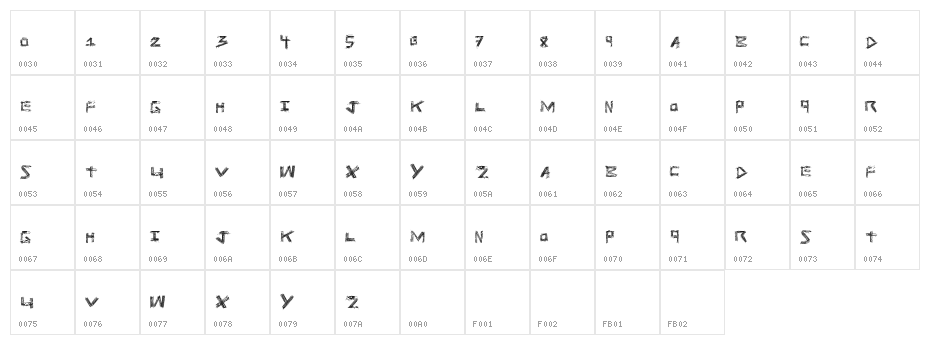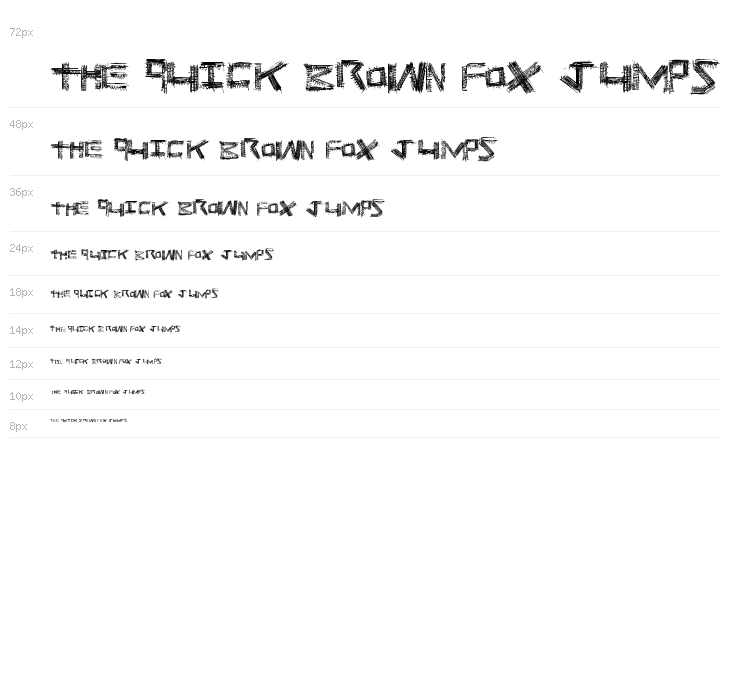
PrisonBreak Font
| Stil general | Urban, Edgy, Rebellious |
| Proiecte propuse | Ideal for album covers, street art designs, posters, and edgy branding projects. |